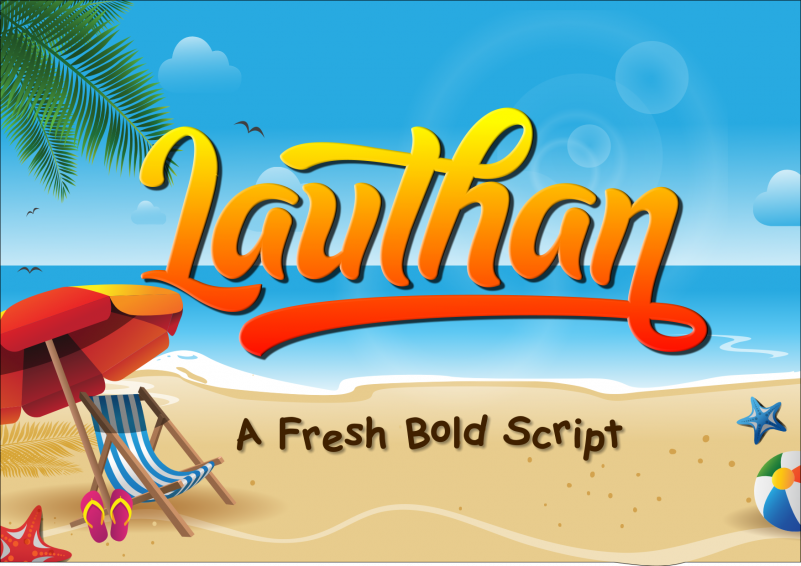
Lauthan Script Font – Download Grátis
Lauthan Script Font é uma fonte elegante para projetos digitais que exigem aprimoramento visual. Esta fonte bold tem um ar inovador e é perfeitamente adaptável à sua próxima criação gráfica. Ideal tanto para estilos modernos quanto para os mais tradicionais, ela oferece flexibilidade em uma variedade de projetos. As utilizações potenciais incluem logotipos, cartões de visita, avisos, embalagens de produtos, materiais de mídia social, rótulos e até mesmo designs de calçados. Com seu design único, Lauthan Script Font atende a um leque vasto de necessidades gráficas. O acesso aos caracteres maiúsculas, minúsculas, números e sinais gráficos faz dela uma escolha excelente para qualquer projeto de identidade visual ou design editorial. Além disso, sua multilínguagem garantirá que você tenha uma solução versátil em português e outros idiomas. Para projetos com mais requisições, a fonte ainda inclui recursos do tipo OpenType, como alternativas para caracteres (alternates) e ligações de caracteres (ligatures). Com um design leve e moderno, Lauthan Script Font é perfeita tanto para novos usuários quanto para designers experientes que buscam uma fonte que combina estética clássica com modernidade. É a escolha perfeita para quem deseja dar um toque de elegância em seus projetos digitais.
Designer: nurfdesigns